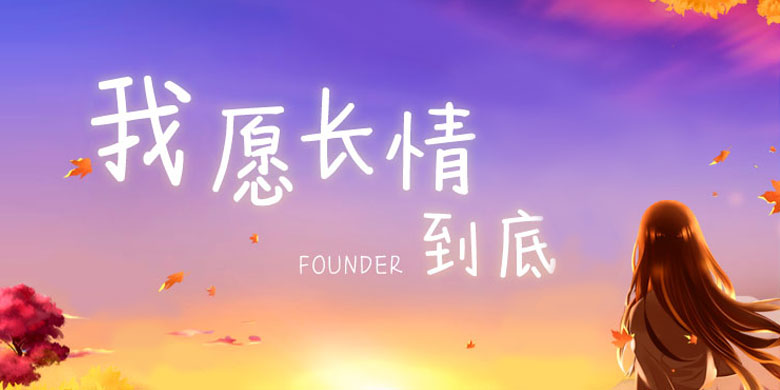
方正手迹-我愿长情到底
字体品牌: 方正手迹 设计师:刘晔 字体分类:创意书写 字体属性:精品字 字符集:大陆简体(GB2312-80) 发布时间: 2020
我愿长情到底是一款风格特别的手写体。该字体整体瘦高,笔画平直、转折果断、分布均匀。适用于文艺类和可爱类的书刊、品牌广告和产品包装设计,以及社交网络的个性化用字。